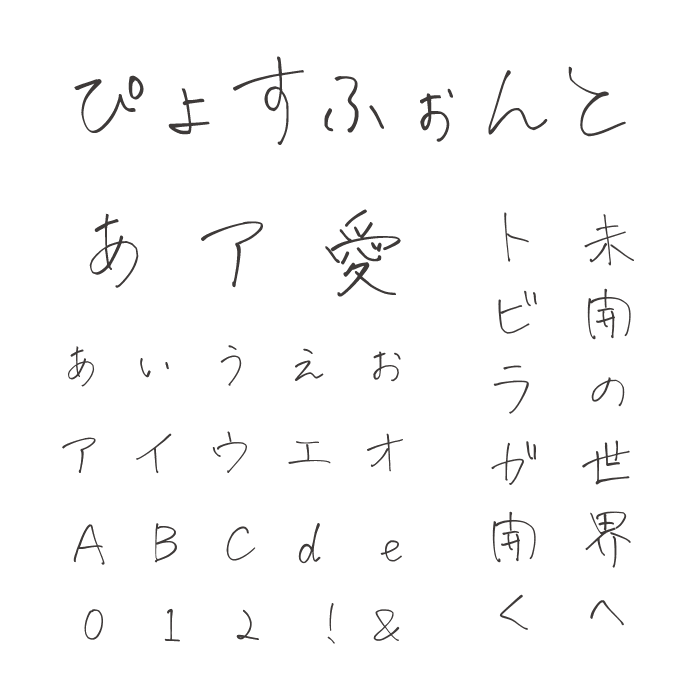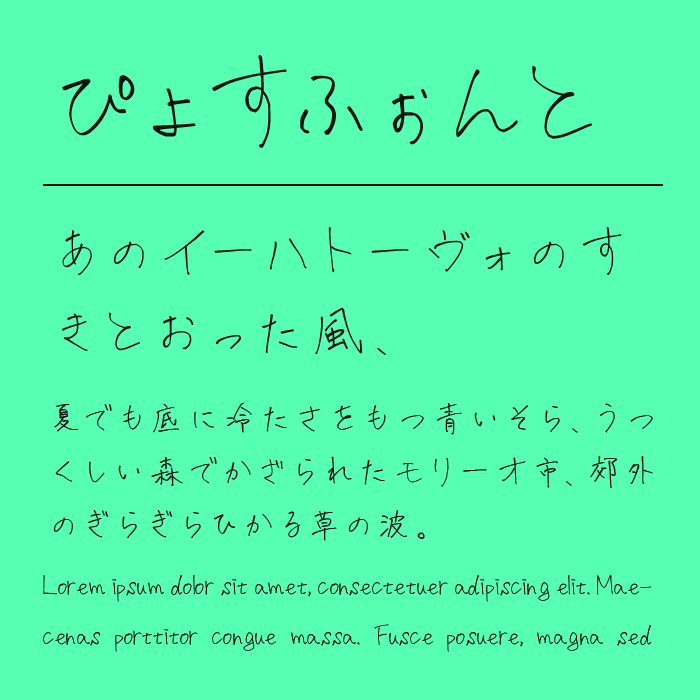
ぴょすふぉんとは、細く軽やかな線で構成された、ゆるい手書き感が魅力の手書きフォントです。
力を入れすぎずにサラサラっと書いたような筆致が心地よく、気取らない自然体の雰囲気があります。文字の大きさや傾きにほんの少し揺らぎがあり、デジタルらしさを抑えた人懐っこい空気感を生み出しています。
文字そのものが柔らかい空気を持っているため、見る人との距離感をぐっと近づけてくれるようなやわらかさがあります。肩の力を抜いたラフなデザインにぴったりなフォントです。